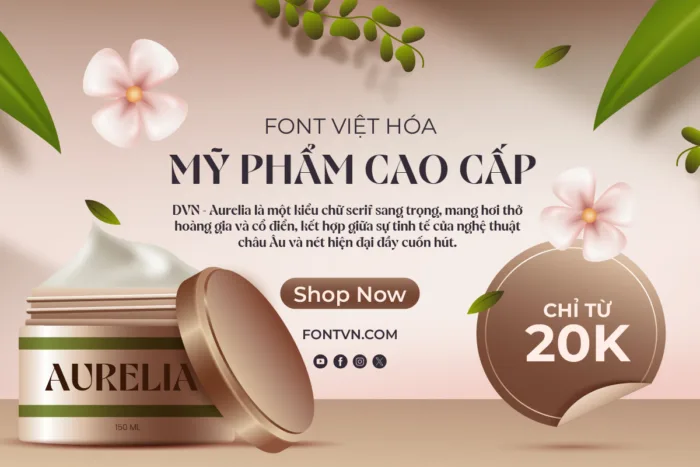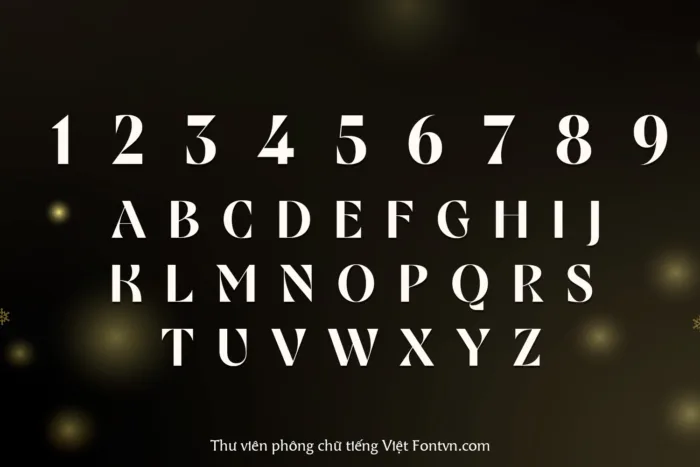
DVN Aurelia Việt hóa – Font chữ Serif sang trọng, hoàng gia
DVN – Aurelia là một kiểu chữ serif sang trọng, mang hơi thở hoàng gia và cổ điển, kết hợp giữa sự tinh tế của nghệ thuật châu Âu và nét hiện đại đầy cuốn hút. Với độ tương phản cao giữa nét dày và nét mỏng, DVN – Aurelia tỏa ra sự thanh lịch, quyền quý, lý tưởng cho các thiết kế thời trang, tạp chí cao cấp, thương hiệu xa xỉ và ấn phẩm nghệ thuật.
Lấy cảm hứng từ cái tên “Aurelia” – mang ý nghĩa “vàng son” trong tiếng Latin, font chữ này thể hiện vẻ đẹp rực rỡ và trường tồn. Các đường nét mềm mại nhưng sắc sảo giúp DVN – Aurelia giữ được sự cân bằng giữa cổ điển và hiện đại, tạo cảm giác vừa uy nghiêm, vừa lôi cuốn. Đây là lựa chọn hoàn hảo cho những thiết kế cần sự đẳng cấp, từ logo, tiêu đề đến bao bì sản phẩm. Với DVN – Aurelia, mọi tác phẩm đều toát lên nét đẹp quý tộc và tinh tế.